도장 이미지 만들기 폰트 추천 Best 5 – 결재용, 직인, PNG 파일
비대면 업무가 일상이 된 2026년, 여전히 결재 문서의 마지막 정점은 ‘도장’입니다. 단순히 빨간 원을 그리는 것을 넘어, 조직의 권위와 개인의 신뢰를 담아낼 수 있는 최적의 폰트 5종 추천과 배경이 투명한 고품질 PNG 파일 제작법을 상세히 공개합니다. 전문가 수준의 결과물을 얻고 싶다면 지금 바로 확인해 보세요!
안녕하세요! 오늘은 사무직 직장인이라면 한 번쯤 고민해봤을 법한 ‘디지털 도장 이미지’에 대해 깊이 있게 다뤄보려고 합니다. 사실 저도 처음 전자결재 시스템을 도입했을 때는 대충 기본 폰트로 이름을 쓰고 빨간 테두리를 둘러서 냈거든요. 그런데 다른 분들의 깔끔하고 정갈한 직인을 보니 제 도장이 유독 ‘가짜’처럼 느껴져서 얼굴이 화끈거렸던 기억이 납니다.
한국의 비즈니스 환경에서 도장은 단순한 그림이 아니라, 개인의 의사와 조직의 결정을 증명하는 가장 강력한 시각적 기호입니다. 디지털 전환 시대에 들어서며 종이에 찍던 인영(印影)이 이미지 파일로 변모했지만, 그 안에 담긴 ‘시각적 신뢰’의 가치는 변함이 없습니다. 오늘 이 글을 통해 저작권 걱정 없는 안심 글꼴 선택부터, 파워포인트와 온라인 도구를 활용한 제작 노하우까지 모두 전해드리겠습니다. 😊
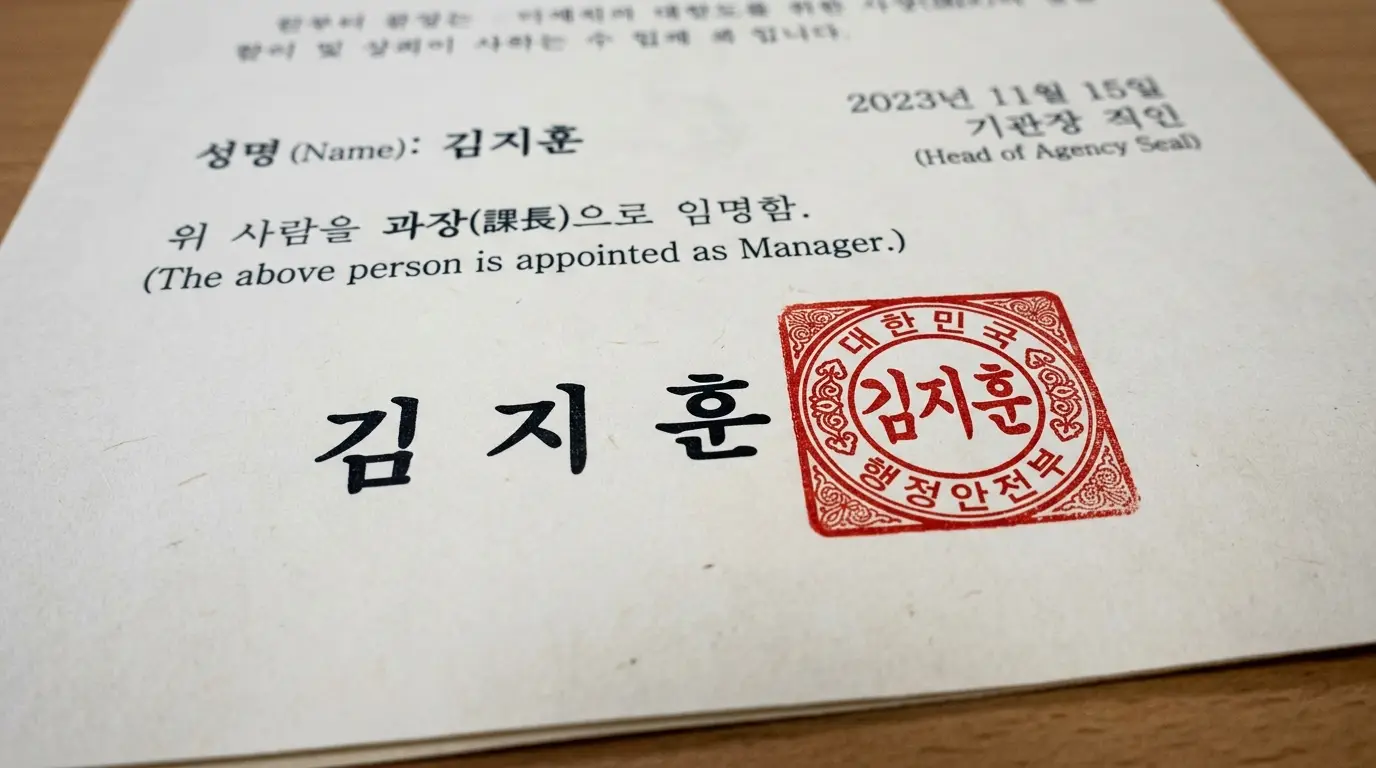
도장 이미지용 최적 폰트 Best 5 선정 기준 💡
도장 서체를 고를 때 가장 중요한 것은 무엇일까요? 심미성도 중요하지만, 디지털 문서에서는 가독성과 법적 규격의 적합성, 그리고 무엇보다 라이선스의 안전성이 확보되어야 합니다. 이번 가이드에서는 이 세 가지 요소를 완벽하게 충족하는 5가지 서체를 엄선했습니다.
| 순위 | 서체 명칭 | 주요 특징 | 권장 용도 |
|---|---|---|---|
| 1 | HJ한전서 B | 전통 전서체의 현대적 구현 | 정통 결재인, 법인 인감 |
| 2 | Noto Serif (본명조) | 방대한 한자 지원 및 깔끔한 획 | 범용 결재인, 한자 도장 |
| 3 | KCC안중근체 | 힘 있는 붓글씨 질감 | 개인 낙관, 개성 있는 서명 |
| 4 | 순바탕 | 정갈하고 신뢰감 있는 구조 | 공식 행정 문서, 교육용 |
| 5 | 학교안심 상장 | 고전 활판 인쇄의 단단함 | 인증서 및 상장 직인 |
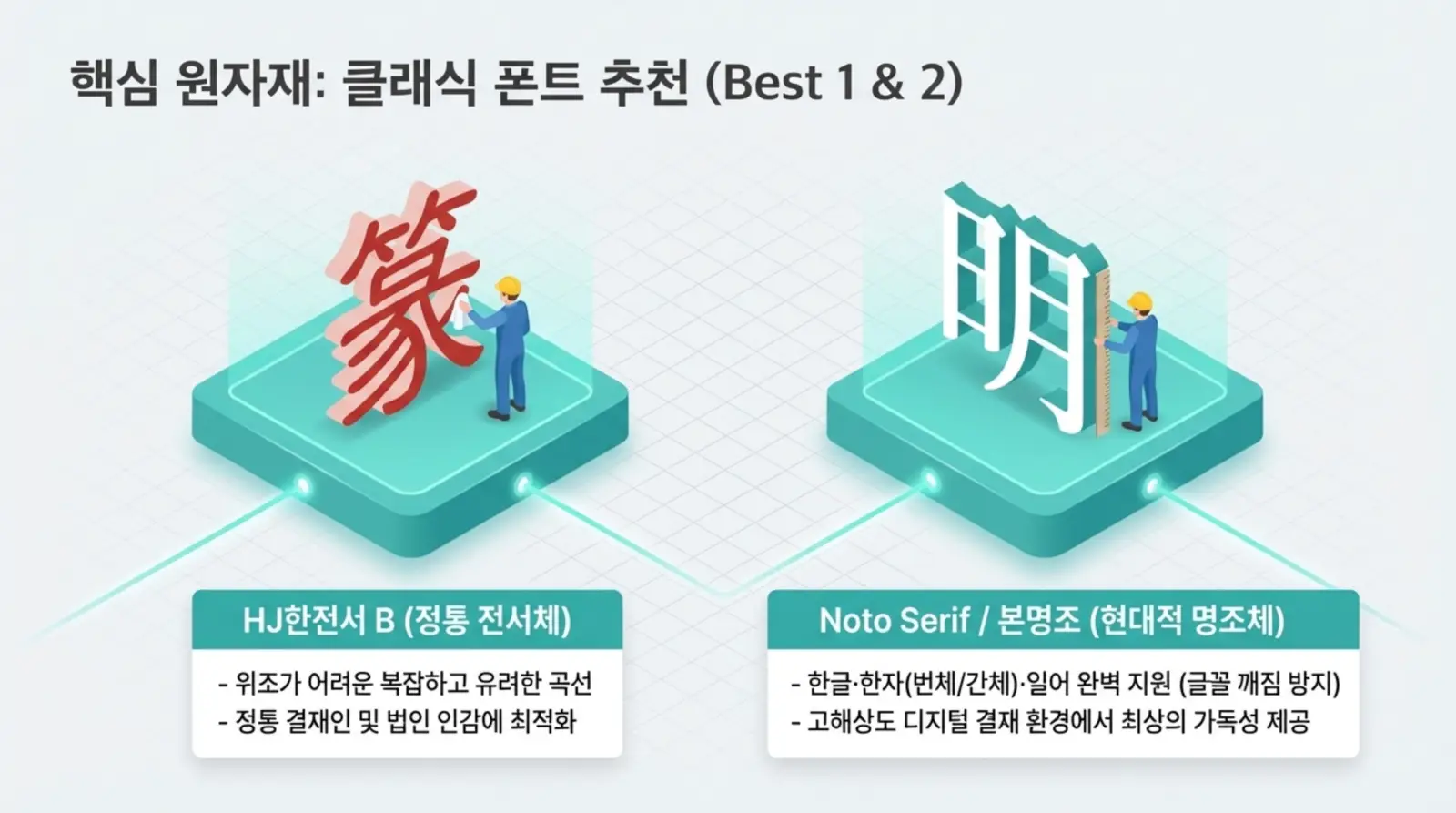
추천 폰트 상세 분석: 왜 이 서체들인가? 📊
1. HJ한전서 B: 정통성과 위조 방지의 미학
HJ한전서 B는 도장 제작 시 가장 먼저 거론되는 서체입니다. 전서체 특유의 복잡한 구조와 유려한 곡선은 도장 틀 안에 배치되었을 때 시각적 밀도를 높여주는데, 이는 과거 아날로그 도장이 가졌던 위조 방지 기능을 디지털에서도 심미적으로 재현합니다. 특히 한자 성명을 넣었을 때 압도적인 권위감을 줍니다.
2. Noto Serif (본명조): 기술적 완벽함
구글과 어도비가 만든 이 서체는 한글, 한자, 일어를 모두 포함하는 방대한 글자 수를 자랑합니다. 기존 서체들이 희귀한 한자를 지원하지 못해 도장 이미지 생성 시 글자가 깨지는 문제를 완벽하게 해결합니다. 고해상도 모니터에서도 획의 마무리가 깔끔하여 현대적인 전자 결재 환경에 가장 적합합니다.
3. KCC안중근체: 역사적 기개와 예술성
안중근 의사의 실제 필체를 바탕으로 제작된 이 서체는 붓글씨 특유의 힘 있는 필치가 살아 있습니다. 일반적인 활자체와 달리 섬세한 질감이 느껴져서, 예술적 용도의 낙관이나 개성 있는 개인 결재인을 만들 때 최상의 선택입니다. 공공누리 제1유형으로 출처만 명시하면 상업적 이용이 가능해 법적으로도 매우 안전합니다.
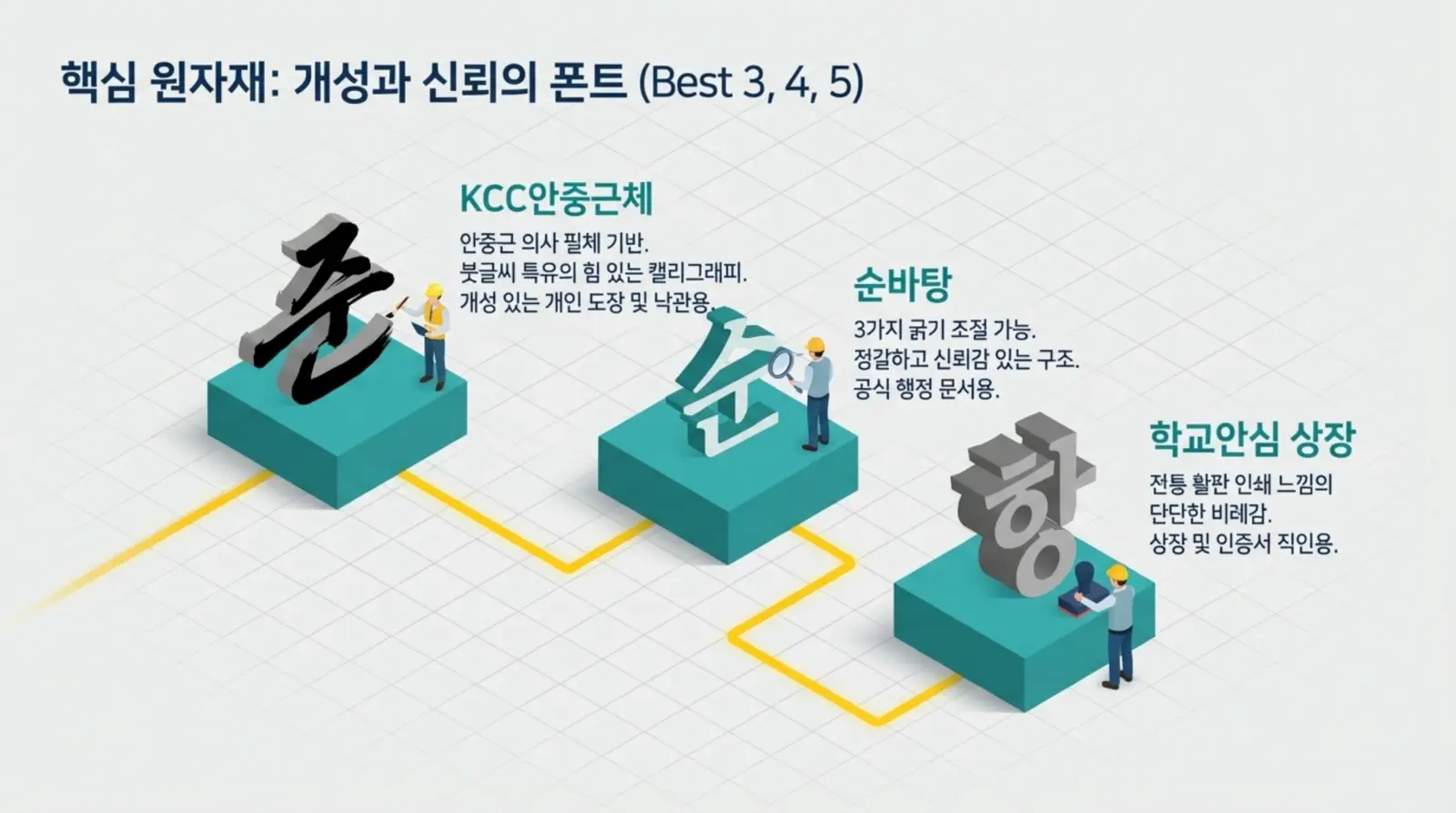
디지털 도장 제작 시 반드시 지켜야 할 규격 📏
멋진 도장을 만드는 것만큼 중요한 것이 법적 기준입니다. 인감증명법 시행령 제6조에 따르면, 도장의 크기는 가로·세로 각각 7mm 이상 30mm 이내여야 합니다. 디지털 파일에서도 이를 고려하여 제작해야 나중에 문서를 인쇄했을 때 실제 도장과 괴리감이 생기지 않습니다.
단계별 도장 이미지 제작 방법론 👨💻
가장 추천하는 방법은 파워포인트(PPT)를 활용하는 것입니다. 포토샵이 없어도 충분히 고품질의 투명 PNG 파일을 만들 수 있거든요.
- 도형 및 텍스트 구성: [삽입] > [도형]에서 원이나 사각형을 그리고 ‘채우기 없음’, ‘윤곽선 빨간색’으로 설정합니다. 그 안에 텍스트 상자를 만들어 성명을 기입합니다. (추천 폰트 사용!)
- 그림으로 변환: 도형과 텍스트를 모두 선택해 복사(Ctrl+C)한 뒤, 마우스 우클릭하여 ‘그림으로 붙여넣기’를 선택합니다.
- 질감 효과 적용: 변환된 그림을 선택하고 [그림 서식] > [꾸밈 효과] > [선 그리기]를 클릭합니다. 이렇게 하면 실제 인조가 번진 듯한 아날로그 질감이 살아납니다.
- 배경 제거 및 저장: [그림 서식] > [색] > [투명한 색 설정]을 통해 배경의 흰색을 클릭하여 제거합니다. 마지막으로 ‘그림으로 저장’을 눌러 반드시 PNG 형식으로 저장하세요.
시간이 너무 없다면 Stampng이나 모두싸인 같은 온라인 자동 생성 서비스를 활용하는 것도 방법입니다. 텍스트 입력과 스타일 선택만으로 3초 만에 투명 PNG 파일을 얻을 수 있어 매우 효율적입니다.
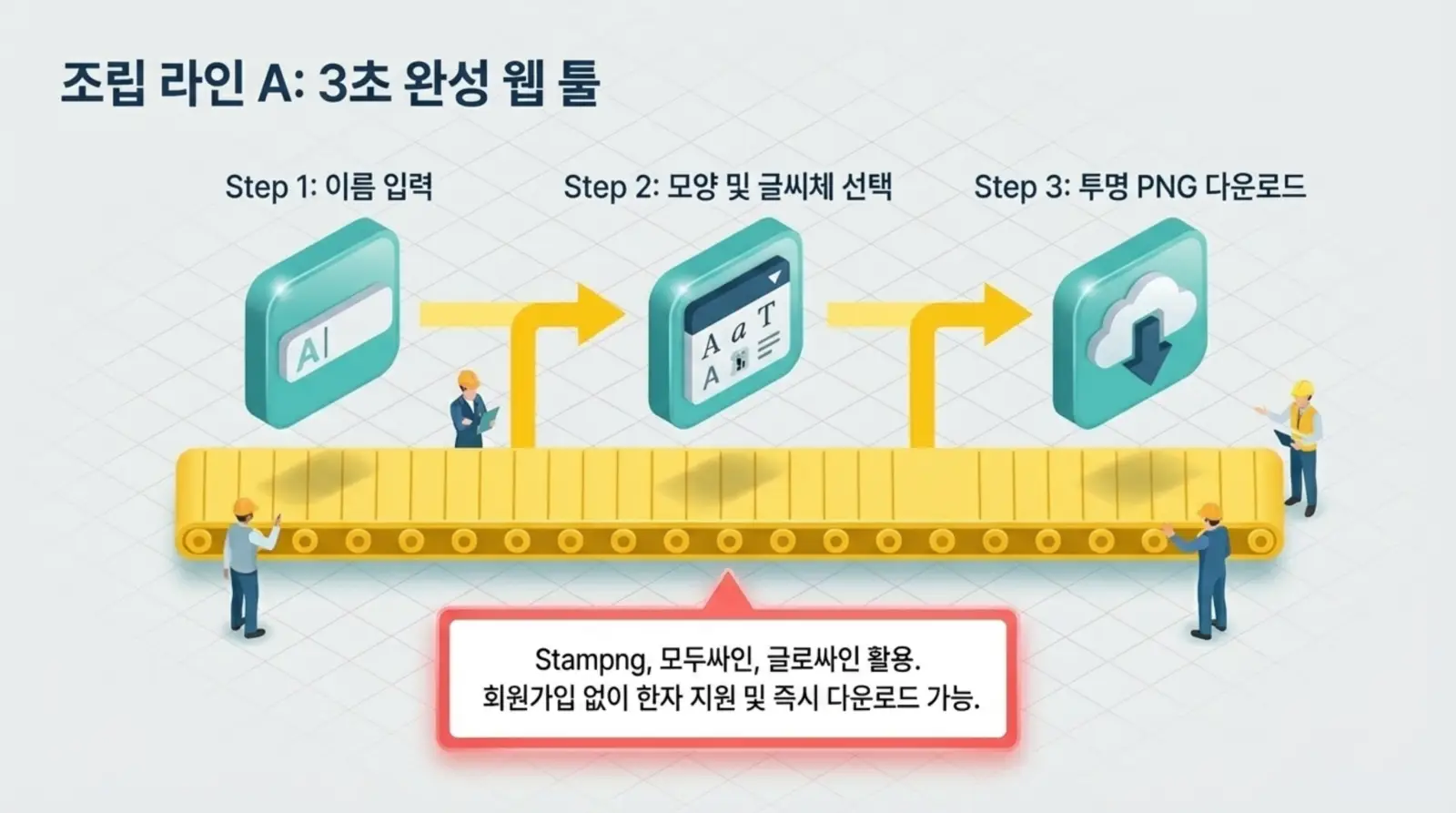
실전 예시: 문서에 자연스럽게 삽입하기 📚
제작된 도장 이미지를 한글(HWP)이나 워드 문서에 넣을 때, 단순히 ‘그림 넣기’만 하면 뒤에 있는 글자가 가려져 어색해 보일 수 있습니다. 이때는 이미지의 배치 옵션을 반드시 조절해야 합니다.
- ✔️ 한글 문서: 개체 속성에서 본문과의 배치를 ‘글 뒤로’로 설정하세요.
- ✔️ 워드/엑셀: 그림 서식의 레이아웃 옵션에서 ‘텍스트 뒤’를 선택하면 이름 위에 도장이 자연스럽게 겹쳐집니다.
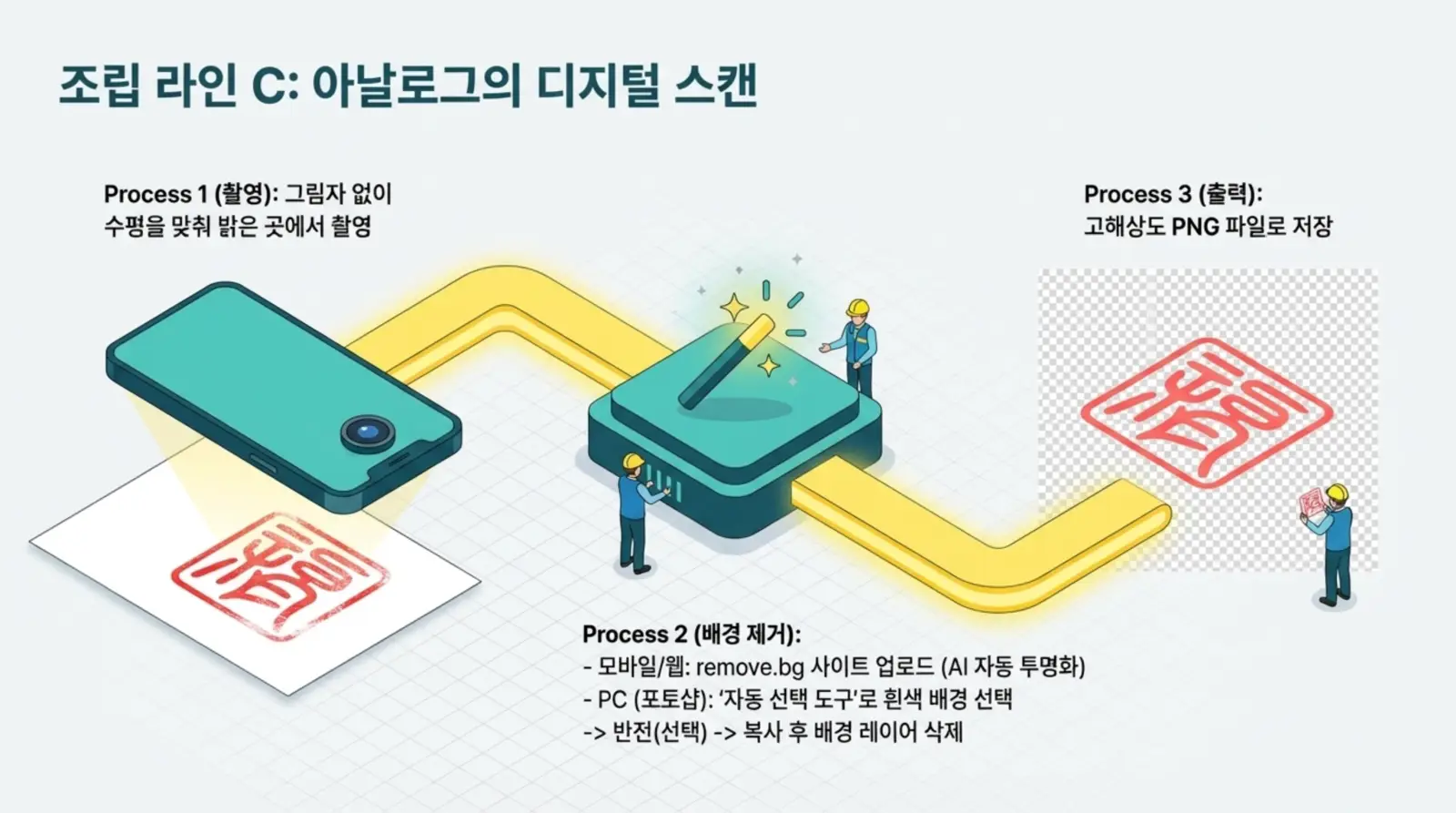
마무리: 디지털 신뢰 자본의 구축 📝
도장의 서체 하나, 1픽셀의 투명도 처리가 모여 문서의 완성도와 권위를 결정짓습니다. 디지털 도장은 단순한 ‘이미지’가 아니라, 비대면 환경에서 여러분의 신뢰를 대신하는 약속의 구현체입니다. 오늘 소개해드린 가이드라인을 통해 전문적이고 세련된 업무 환경을 구축하시길 바랍니다.
📌 도장 이미지 제작 핵심 요약